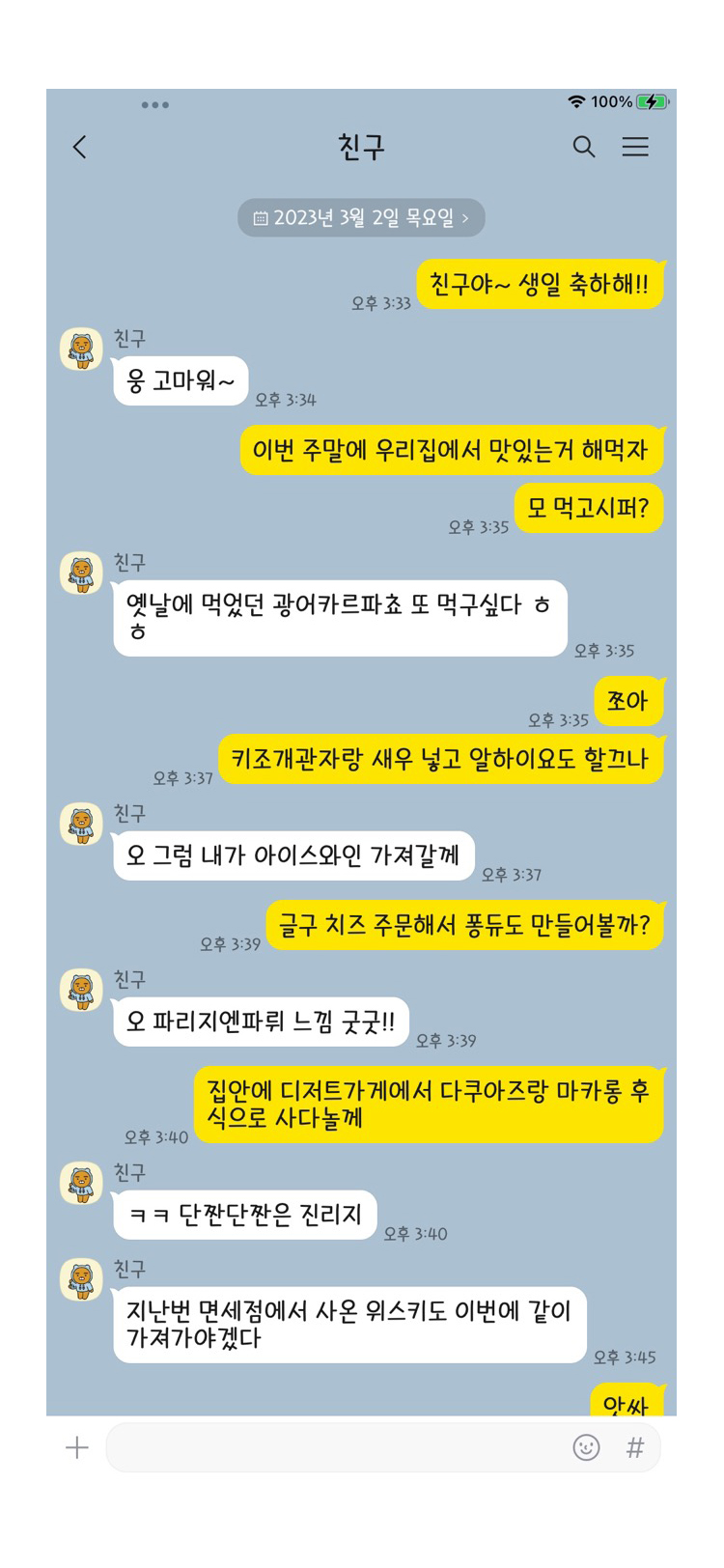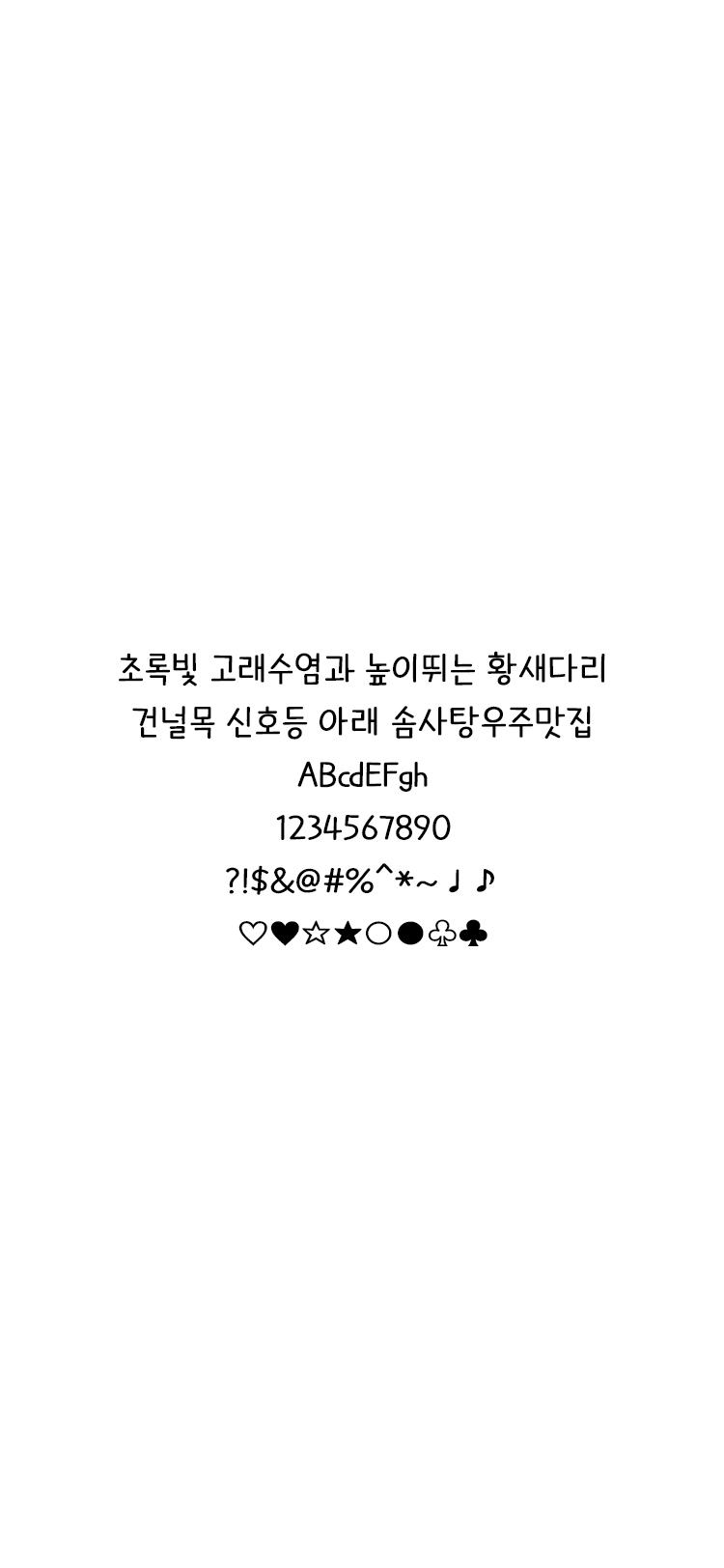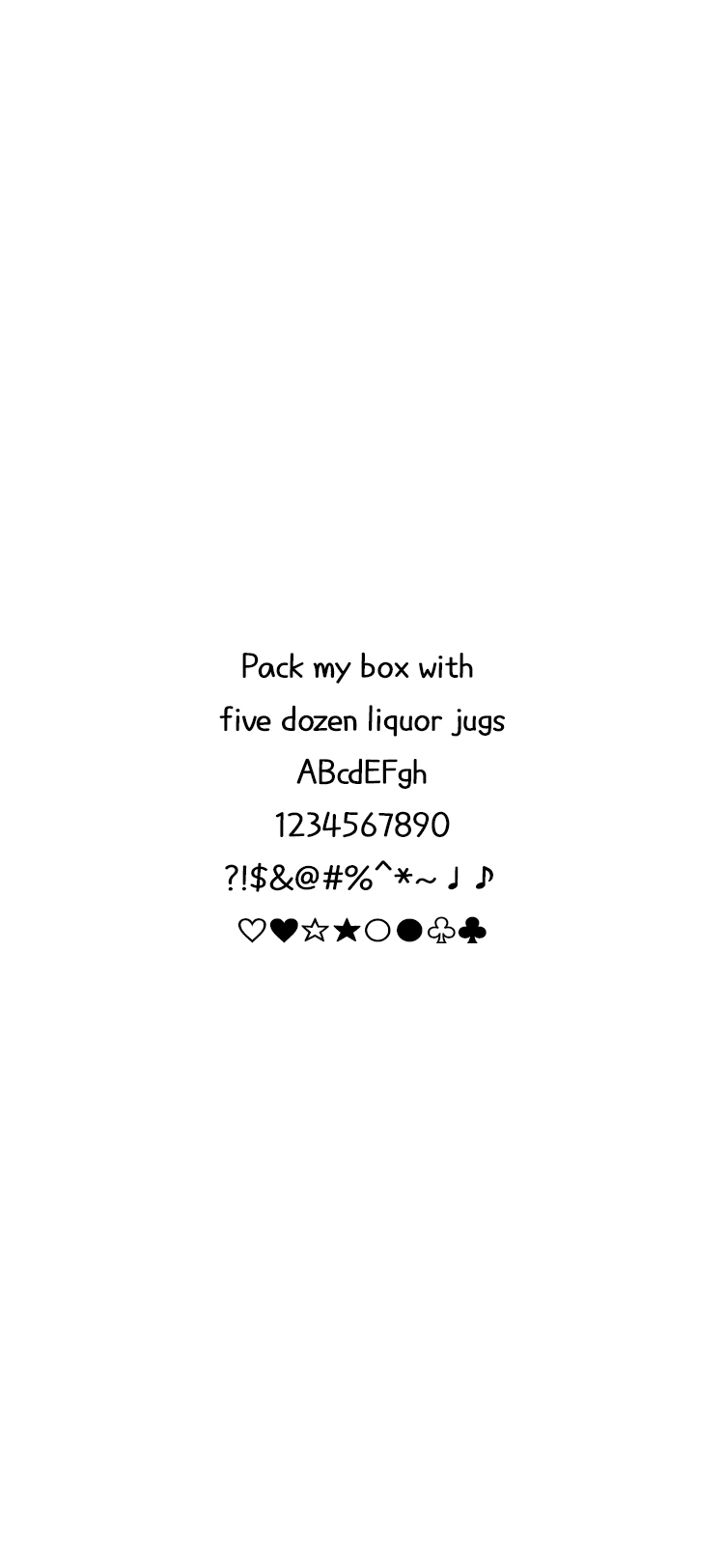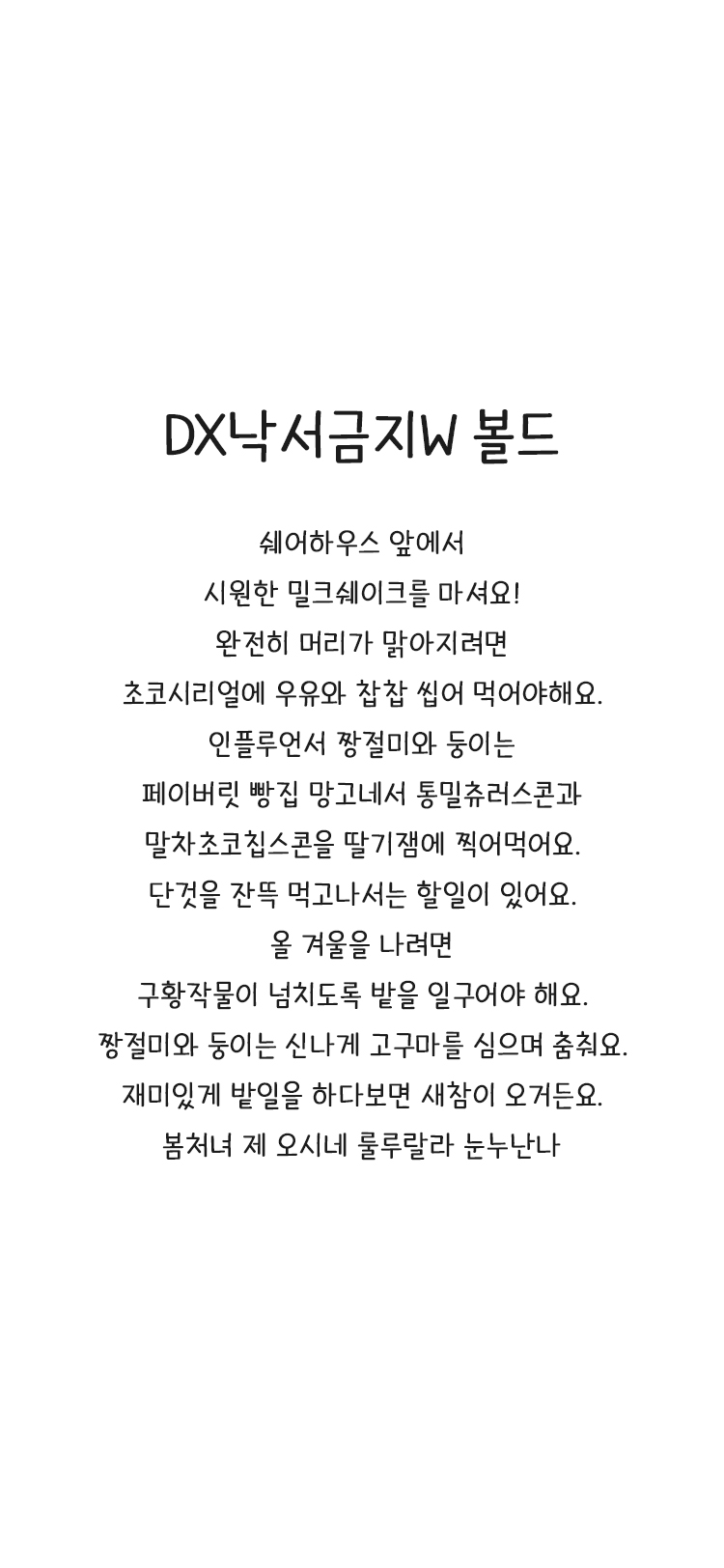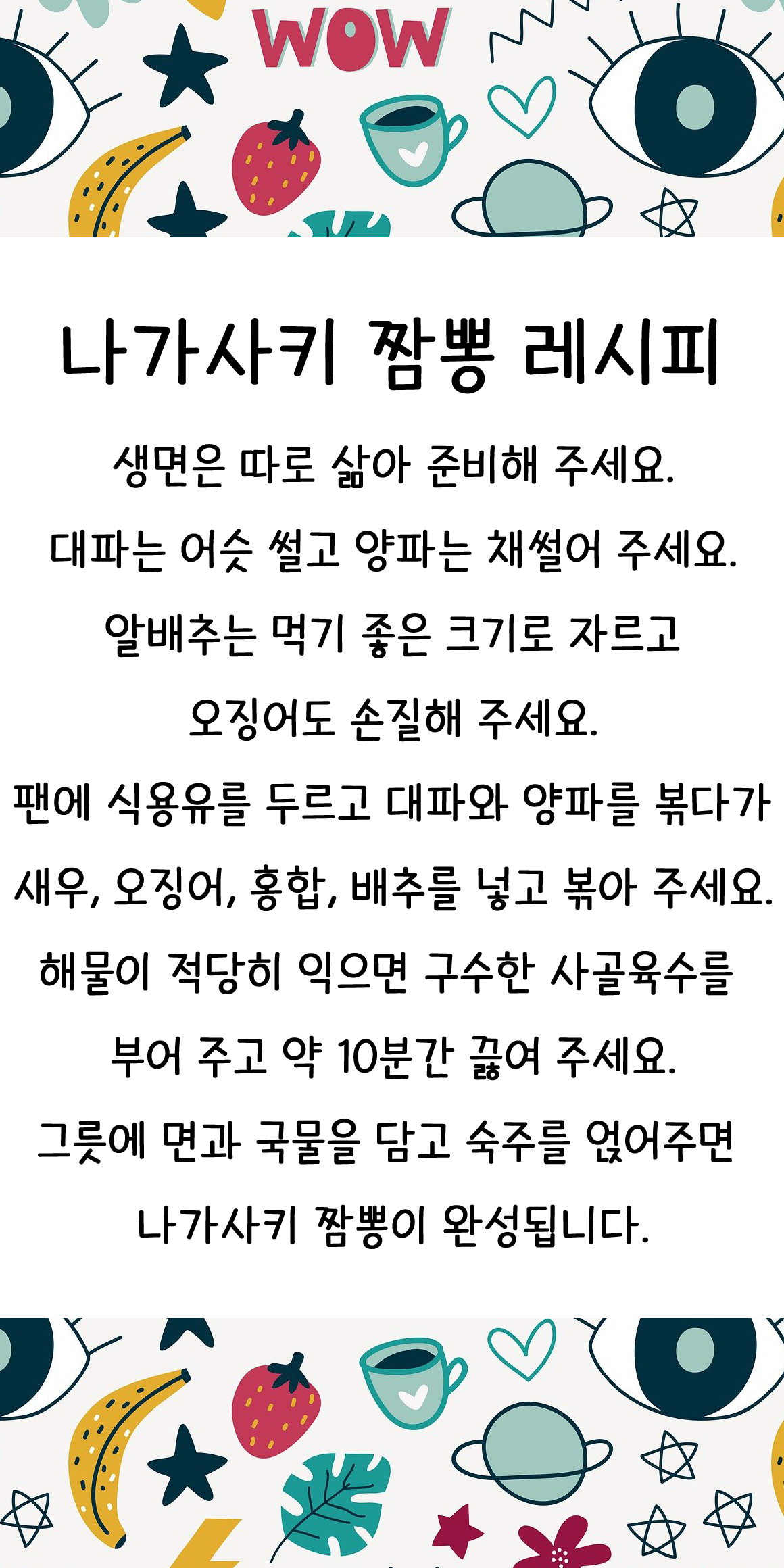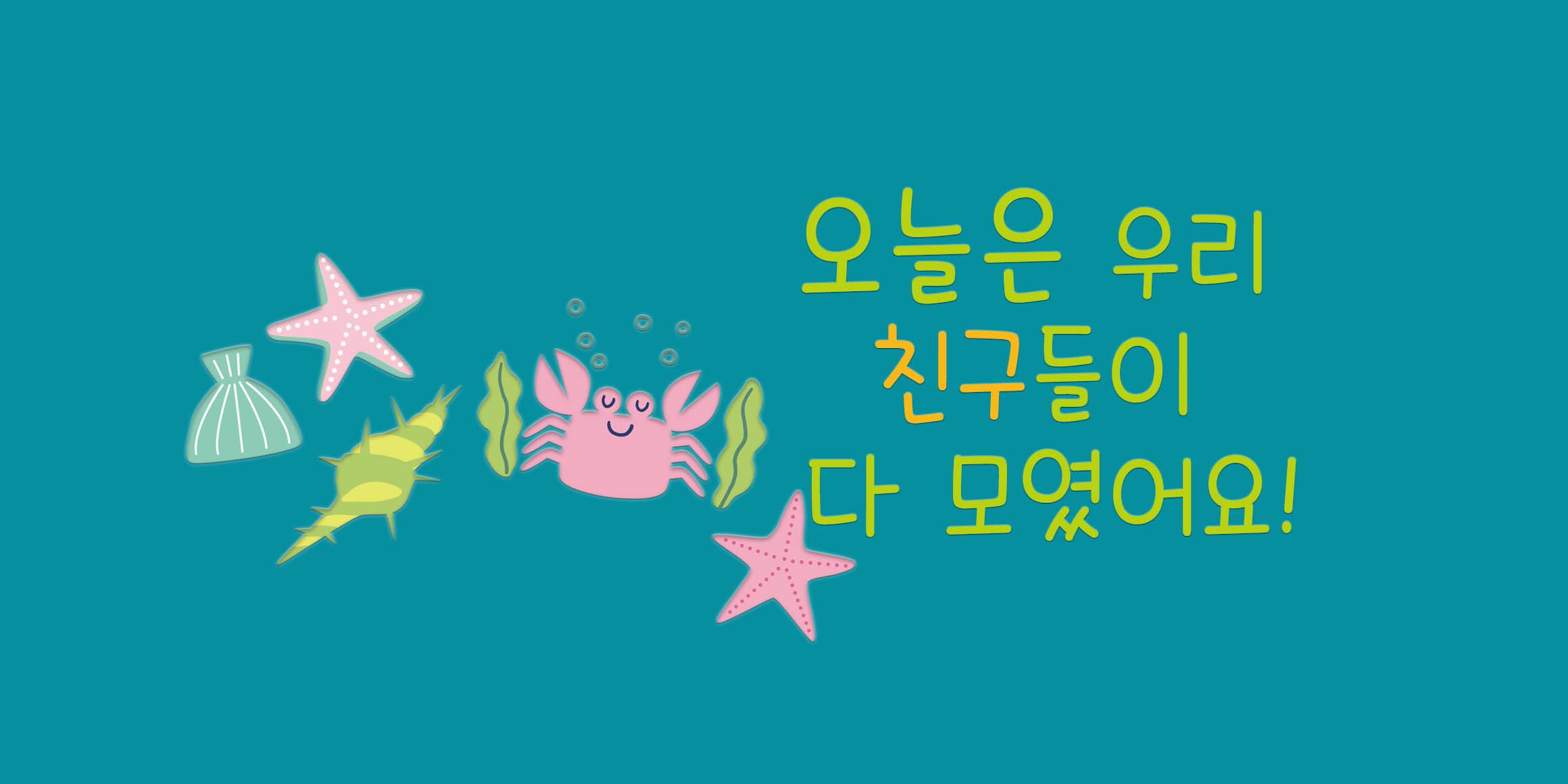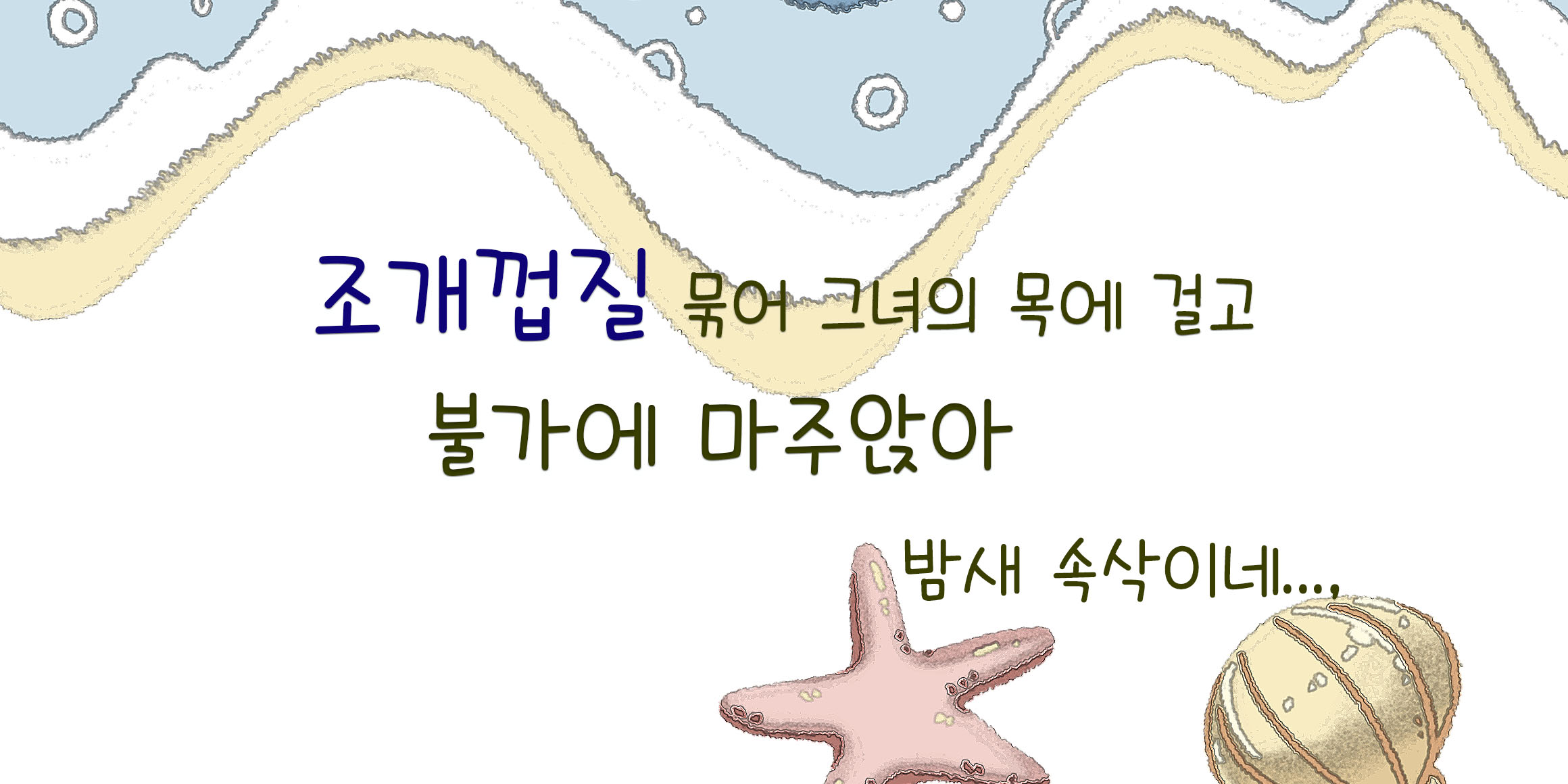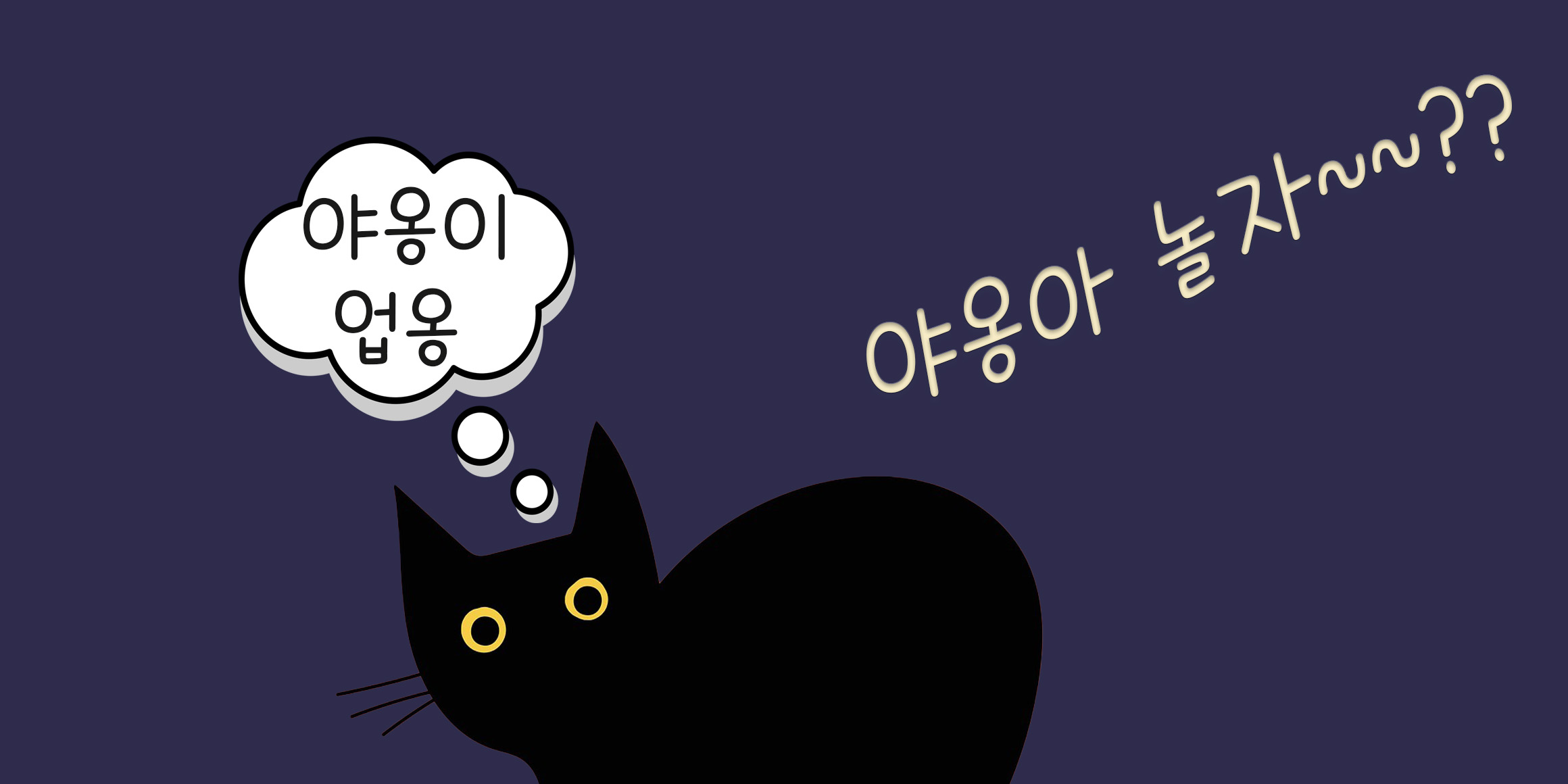
DX낙서금지WStd Bold
한글자 한글자 또박또박 잘쓰기 위해서 정성을 드린 손글씨의 느낌이 그대로 묻어나 있는 폰트이다. 초성이 종성보다 크게 설계되어 있고, 전체적인 분위기는 자유 분방하면서도 글줄에서는 리듬감과 재미와 멋을 느낄 수 있다. 긴 문장에서도 가독성이 잘 되도록 제작되어 있어서 자막으로 사용하기에도 좋은 폰트이다.